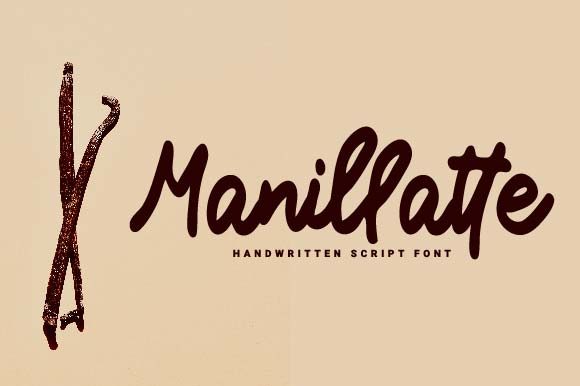
Creativefabrica Manillatte Font
Manillatte - это смелый и плавный рукописный шрифт.
Чистый и немного причудливый, этот шрифт идеально подходит для всех ваших логотипов, брендинга, социальных сетей и ремесленных DIY-проектов.